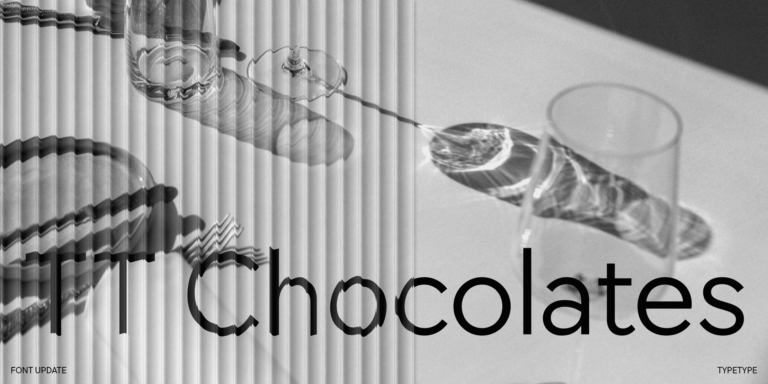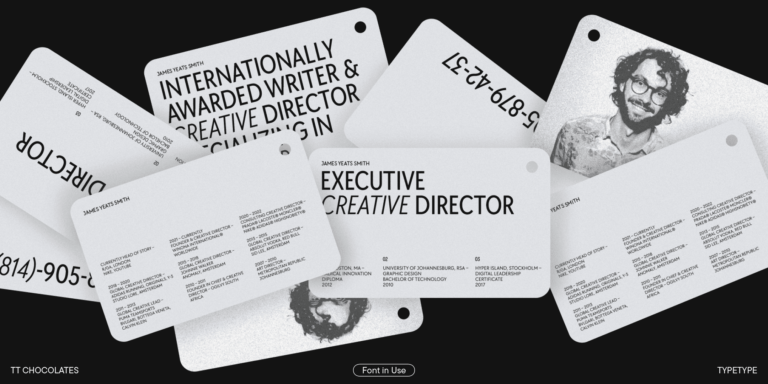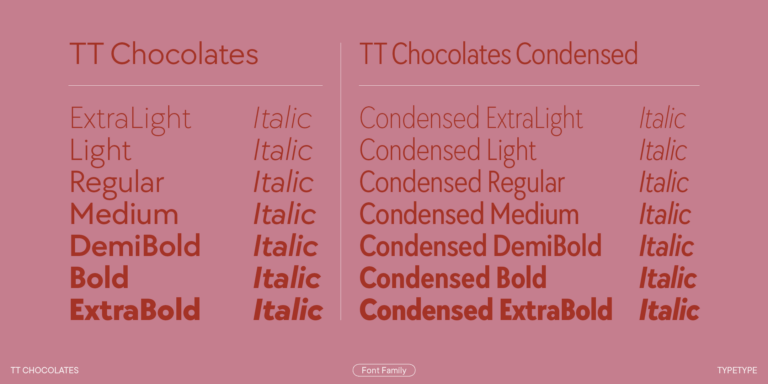
Memimas-Schriften
Die Schrift TT Chocolates besteht aus 14 Fonts: 7 Strichstärken und 7 Obliques. Sie bietet erweiterte Sprachunterstützung und nützliche Features.